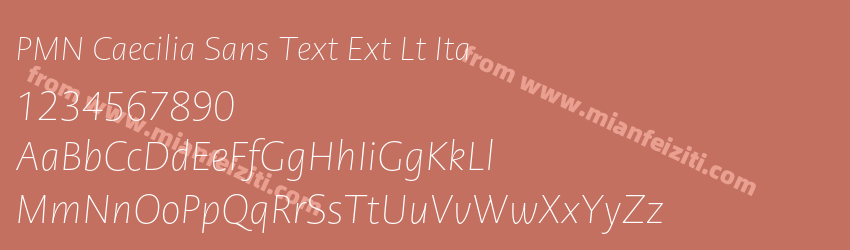
PMN Caecilia Sans Text Ext Lt Ita
字体名称: PMN Caecilia Sans Text Ext Lt Ita
Postscript名称: PMNCaeciliaSansText-ExtLtIta
本款“PMN Caecilia Sans Text Ext Lt Ita”是一款书写很新颖的字体,字体大方,适合各种设计作品使用!欢迎下载!